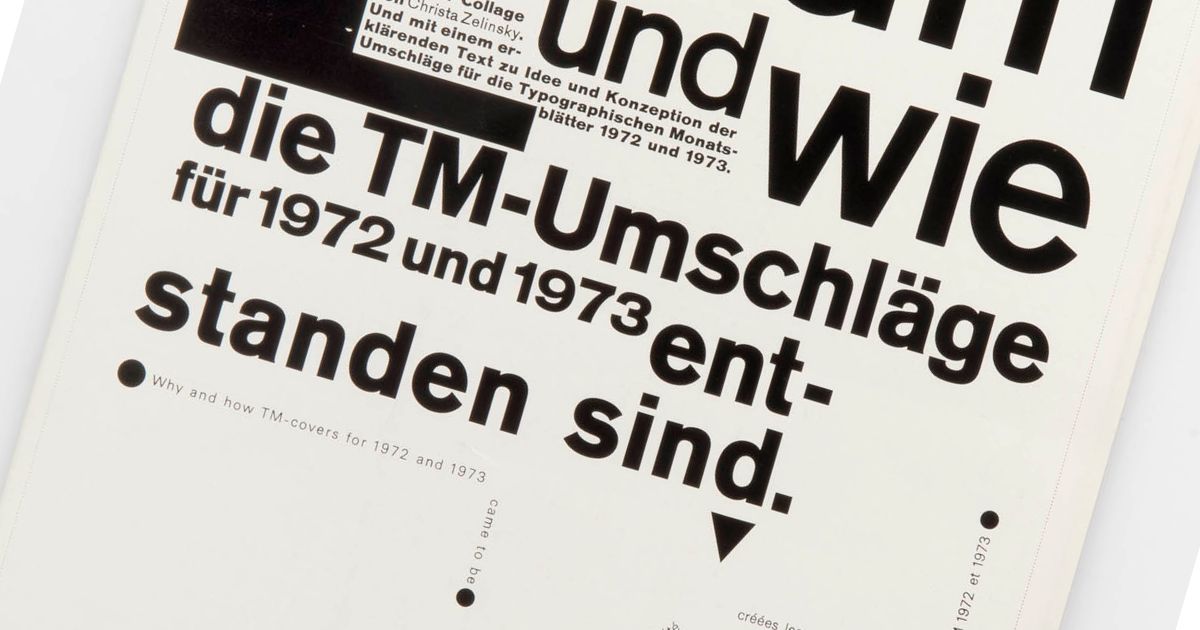
Este archivo digital es un tesoro de la tipografía y el diseño
El TM Research Archive recopila todos los números de la revista Typographische Monatsblätter, pieza clave de la historia de la tipografía
Si hubo un seísmo en la historia del diseño gráfico durante el siglo XX esa fue la aparición y difusión del Estilo Tipográfico Internacional, movimiento de origen ruso, holandés y alemán pero que se desarrollaría especialmente en Suiza durante y en los años posteriores a la Segunda Guerra Mundial.
Con su búsqueda de la unión entre forma y contenido, su persecución de la simplicidad y su interés por el diseño tipográfico, el Estilo Internacional influiría tan profundamente en el diseño mundial que sus máximas llegan hasta el día de hoy.
Y si hubo una revista especialmente conectada a este movimiento, esa fue la Typographische Monatsblätter, cuyas portadas reflejan la evolución estética, cultural y social del diseño durante gran parte del siglo XX. Unas portadas a las que ahora puedes acceder, de forma totalmente gratuita.
El TM Research Archive es una web concebida por la suiza Louise Paradis como proyecto final de máster; se trata de un repositorio que recopila información e imágenes sobre la Typographische Monatsblätter entre los años sesenta y noventa del pasado siglo. Un auténtico tesoro que incluye decenas de portadas, índices de contenidos de cada uno de los números de la revista y biografías detalladas de sus diseñadores y tipógrafos más importantes. Pero eso no es todo.
Un archivo de entrevistas con grandes diseñadores
La web incluye también otro extraordinario recurso: una serie de conversaciones con diseñadores esenciales del siglo XX, presentes de un modo u otro en la revista, como April Greiman, Yves Zimmerman o Christian Mengelt. Se trata de entrevistas en profundidad que fascinarán a los estudiosos del diseño tipográfico suizo, pero también a todos aquellos curiosos que quieran ampliar su rango de conocimientos sobre este periodo esencial de la historia del diseño y la tipografía.